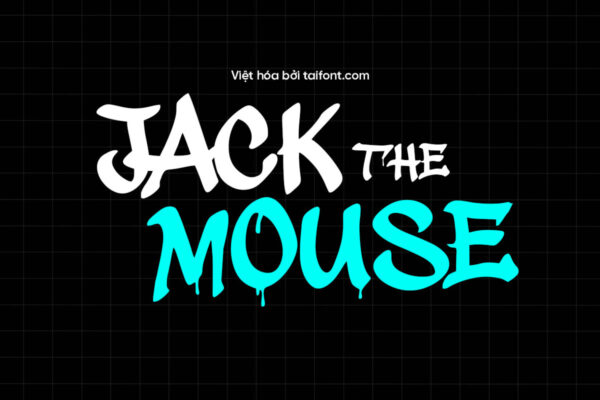
Font Việt hóa TF Jack The Mouse là một trong những lựa chọn hàng đầu cho các nhà thiết kế muốn tạo ra những tác phẩm độc đáo và sáng tạo. Với kiểu nét vẽ đường phố đẹp và độc đáo, font này chắc chắn sẽ giúp bạn tạo ra những thiết kế ấn tượng và thu hút.
Ứng dụng của Font Việt hóa TF Jack The Mouse
Font Việt hóa TF Jack The Mouse có thể được ứng dụng trong nhiều lĩnh vực thiết kế khác nhau, từ thiết kế đồ họa đến thiết kế web và thậm chí là thiết kế in ấn.
Cách sử dụng Font Việt hóa TF Jack The Mouse hiệu quả
Lựa chọn kích thước font phù hợp
Lựa chọn kích thước font phù hợp là một trong những yếu tố quan trọng nhất khi sử dụng Font Việt hóa TF Jack The Mouse. Bạn cần đảm bảo rằng kích thước font của bạn đủ lớn để dễ đọc nhưng không quá lớn để làm cho thiết kế trở nên quá phức tạp.
Lựa chọn màu sắc phù hợp
Lựa chọn màu sắc phù hợp cũng là một yếu tố quan trọng khi sử dụng Font Việt hóa TF Jack The Mouse. Bạn cần đảm bảo rằng màu sắc của bạn phù hợp với thương hiệu và mục tiêu của bạn.
Lợi ích của việc sử dụng Font Việt hóa TF Jack The Mouse
Font Việt hóa TF Jack The Mouse mang lại nhiều lợi ích cho các nhà thiết kế, bao gồm:
- Tạo ra những thiết kế độc đáo và sáng tạo
- Được ứng dụng trong nhiều lĩnh vực thiết kế khác nhau
- Dễ sử dụng và tùy chỉnh
Sai lầm cần tránh khi sử dụng Font Việt hóa TF Jack The Mouse
Để sử dụng Font Việt hóa TF Jack The Mouse hiệu quả, bạn cần tránh một số sai lầm phổ biến, bao gồm:
- Sử dụng kích thước font quá nhỏ hoặc quá lớn
- Sử dụng màu sắc không phù hợp với thương hiệu
- Không tùy chỉnh font để phù hợp với mục tiêu của bạn
Font Việt hóa TF Jack The Mouse là một lựa chọn hoàn hảo cho các nhà thiết kế muốn tạo ra những tác phẩm độc đáo và sáng tạo. Để sử dụng font này hiệu quả, bạn cần lựa chọn kích thước font phù hợp, lựa chọn màu sắc phù hợp và tránh một số sai lầm phổ biến. Hãy tải xuống Font Việt hóa TF Jack The Mouse ngay hôm nay và bắt đầu tạo ra những thiết kế ấn tượng và thu hút!
Font Việt hóa TF Jack The Mouse